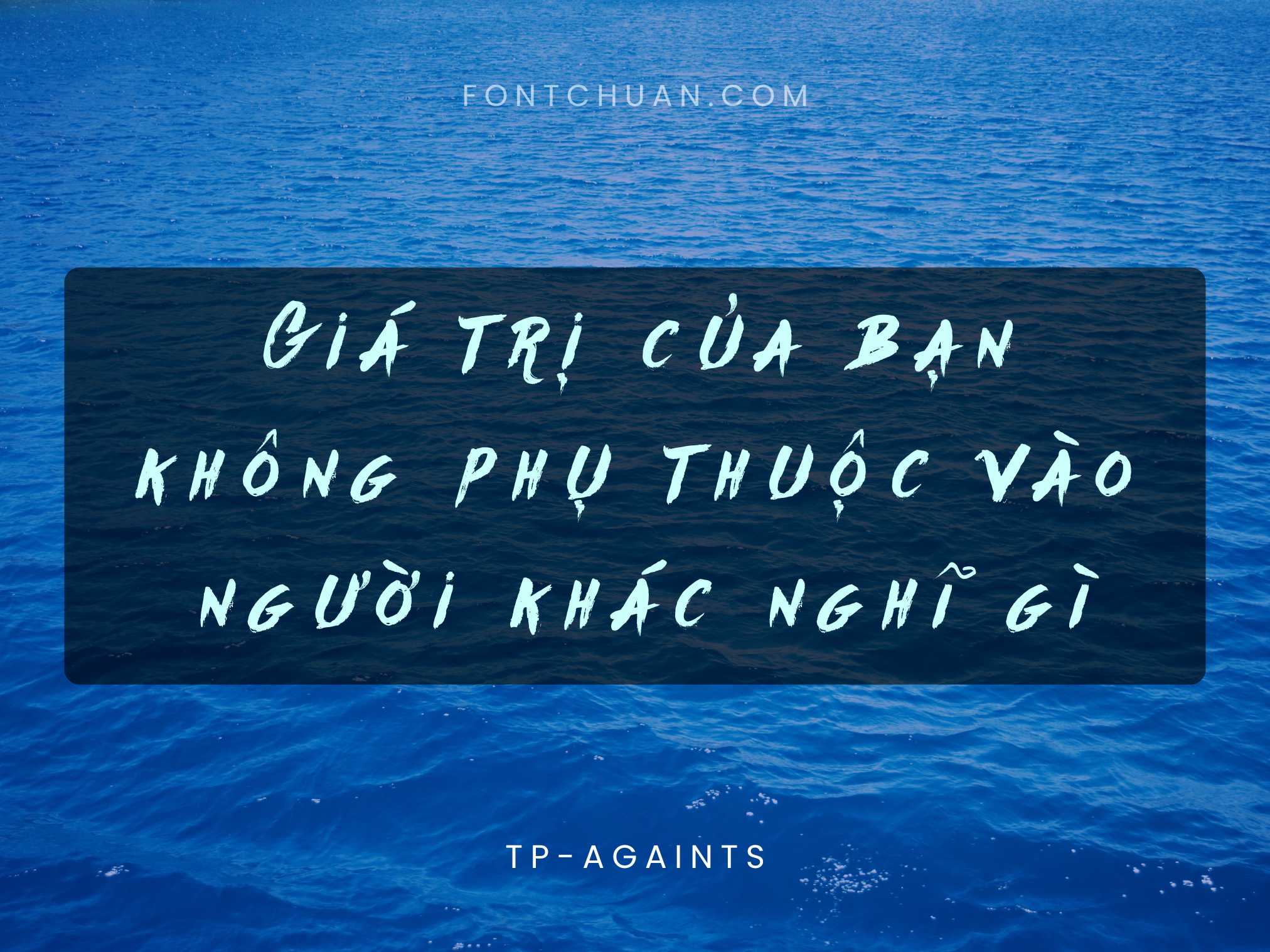
Font TP Againts Việt Hóa
TP-Againts là một font chữ lấy cảm hứng từ nét cọ tay tự nhiên, tạo ra cảm giác mạnh mẽ và phóng khoáng trong thiết kế. Font này được thiết kế bởi Ramandhani Nugraha, mang đến sự độc đáo và sáng tạo cho các dự án thiết kế. Font đã được Việt hóa để hỗ trợ tiếng Việt bởi Tuỳn Pucca, đồng thời hỗ trợ nhiều ngôn ngữ khác, giúp mở rộng phạm vi sử dụng trên toàn cầu. Font này được sưu tầm và chia sẻ bởi thành viên của Font Chuẩn, đáp ứng nhu cầu của người dùng và ứng dụng thực tế vào các dự án thiết kế.
Đặc điểm thiết kế của TP-Againts bao gồm các nét cọ tay tự nhiên, tạo cảm giác phóng khoáng và nghệ thuật. Font này phù hợp cho các ứng dụng như tiêu đề, logo, bao bì sản phẩm và các dự án sáng tạo khác. Các ngành nghề phù hợp bao gồm quảng cáo, nghệ thuật và thiết kế đồ họa.